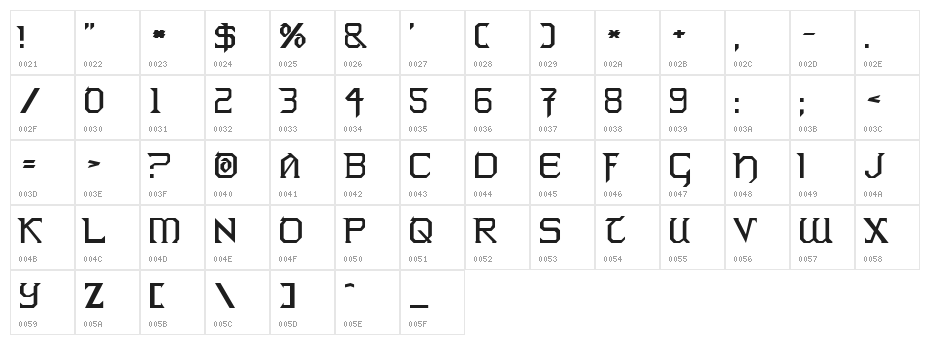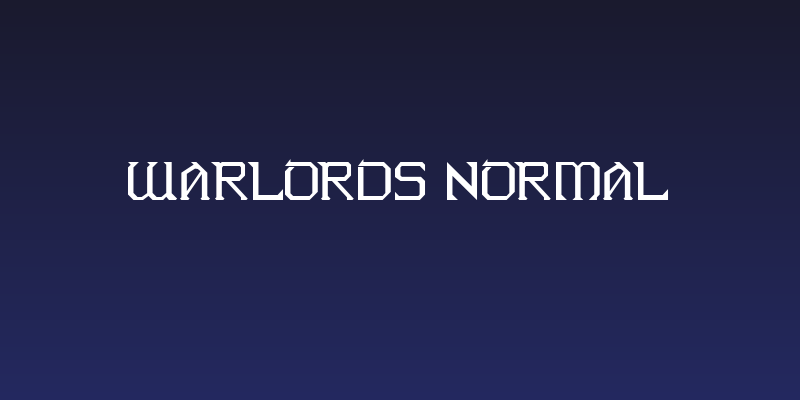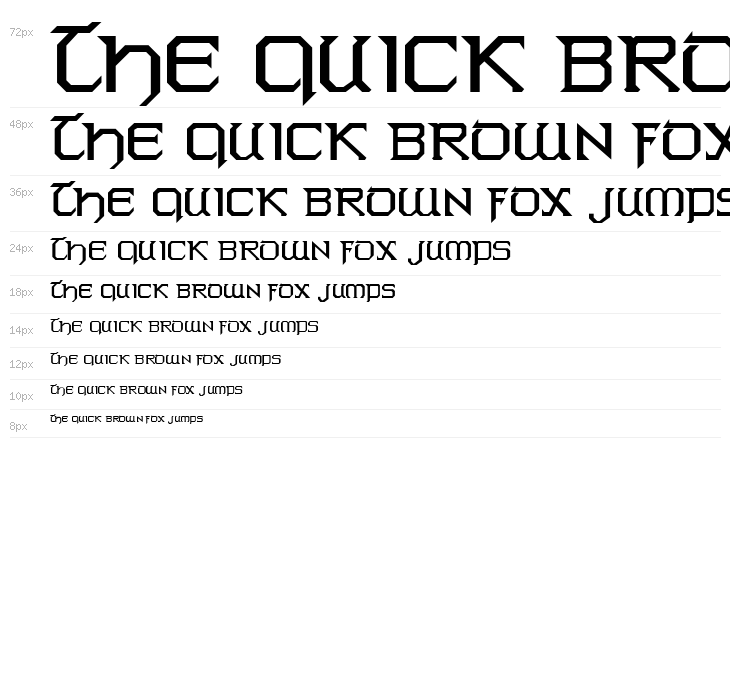
Warlords Normal Font
✎ Gothic
| Proiecte propuse | Ideal for video game titles, movie posters, branding for edgy products, and any project requiring a strong, impactful visual presence. |